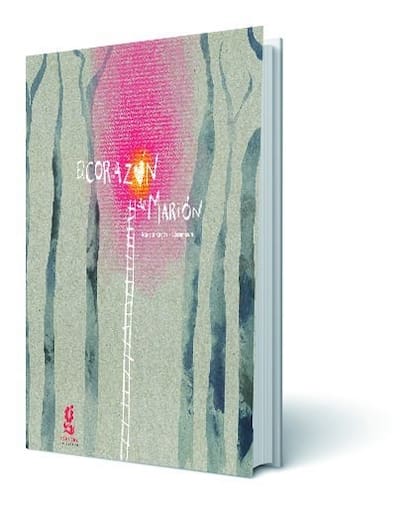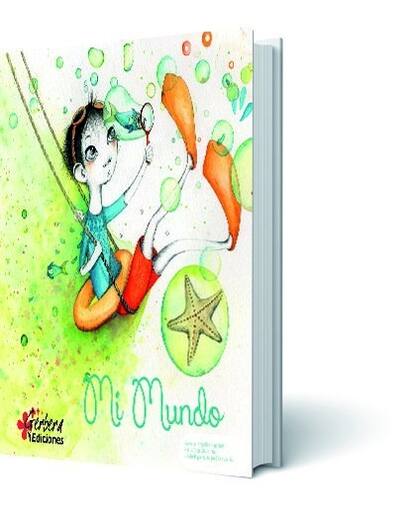
Libros inclusivos: tipografías para chicos disléxicos y con tinta braille
Gerbera es la única editorial que tiene un catálogo infantil que allana dificultades de lectoescritura; este año viajará a la Feria de Guadalajara
Hasta fines de 2011, Fabiana Nolla Portillo trabajó como librera en distintas sucursales de la cadena de librerías Yenny-El Ateneo. Probablemente allí, mediante una relación estrecha con los libros durante diez años, germinó un proyecto que, en 2012, adquirió el nombre de una flor. Gerbera es hoy la primera y única editorial argentina que publica sus libros con tipografía amigable para disléxicos y en tinta braille. En cinco años, la editorial sacó 33 títulos de autores e ilustradores nacionales en distintas colecciones.
"En 2012 editamos los tres primeros títulos -cuenta Portillo, oriunda de Salto y licenciada en Comunicación Social por la Universidad Nacional de Misiones-. Fueron hechos en versión común, hasta que supe que una compañera de escuela de mi hijo no podía leer el libro porque las letras bailaban, giraban y saltaban de renglón." Ésa fue la chispa que la llevó a investigar la posibilidad de editar ejemplares que los chicos disléxicos pudieran leer sin sacrificio. Junto con Silvina Troicovich, una de las autoras del sello, se comunicaron con los responsables de OpenDyslexic (www.opendyslexic.org), creadores de una tipografía especialmente diseñada para los chicos con esta dificultad de lectoescritura. Hicieron el depósito correspondiente y a la calidad literaria de un sello destinado al público infantil sumaron la inclusión. Desde entonces, todos los libros de Gerbera pueden ser leídos por "normolectores" y por disléxicos. Según Portillo, la dislexia afecta a dos de cada treinta niños.
La inclusión es una temática que atraviesa el catálogo del sello. La interculturalidad, las diferencias sociales, los problemas ambientales y las circunstancias de chicos con dificultades para leer son también cuestiones abordadas. El libro más vendido de Gerbera es Serafina e integra la colección Con Nombre Propio, poemas narrativos ilustrados que cuentan historias de chicos que habitan en distintas regiones del país. Serafina es una niña descendiente de quechuas que vive en el norte argentino; Simón, protagonista de otro título, pertenece a una familia guaraní, y Gioia cuenta el romance entre una descendiente de italianos con un joven huarpe en la zona de Cuyo. Los títulos de esta colección están a cargo de la escritora Verónica Álvarez Rivera y de la ilustradora Estrellita Caracol. Mi mundo, de Angélica Pinochet y María José Olavarría, que cuenta la historia de un niño con autismo, se vendió muy bien en pocos meses.
En 2015, una experiencia en una escuela de Ramos Mejía determinó que Portillo se decidiera a incorporar el sistema braille en los libros. "Una nena ciega pasó a leer al frente de la clase uno de nuestros libros, que la madre y la docente auxiliar habían traducido al braille. En lugar de las ilustraciones, habían utilizado telas de distintas texturas", cuenta la editora. A partir de entonces, los libros para niños de 0 a 13 años de Gerbera cuentan con una versión en braille y texturas para apreciar una nueva dimensión de la lectura. "Un papá ciego puede sentarse a leer con su hijo no ciego en el mismo momento el mismo libro", grafica Portillo. Para estos libros, el sello contó con el apoyo de Tiflonexos, una asociación civil sin fines de lucro que trabaja para la inclusión de personas con discapacidad visual en los campos de las nuevas tecnologías, el acceso a la información y la cultura.